今回はアメリカ在住のフリーランスデザイナーが、クラシックでエレガントな欧文フォントをご紹介したいと思います。
クラシックでエレガントなおすすめ英語フリーフォントまとめ【無料&商用利用可能】
Forest Regular Font
エレガントだけど、どっしりとした重厚感もあるフォント。細部まで凝っていますが、読みやすさもキープしているので使いやすいですよ。
Amadeust Inline Font
クラシックな雰囲気あふれるインラインフォント。小さく使うより、思いきり大きく使った方が、ラインがハッキリわかって素敵です。
Arbatosh Regular Font
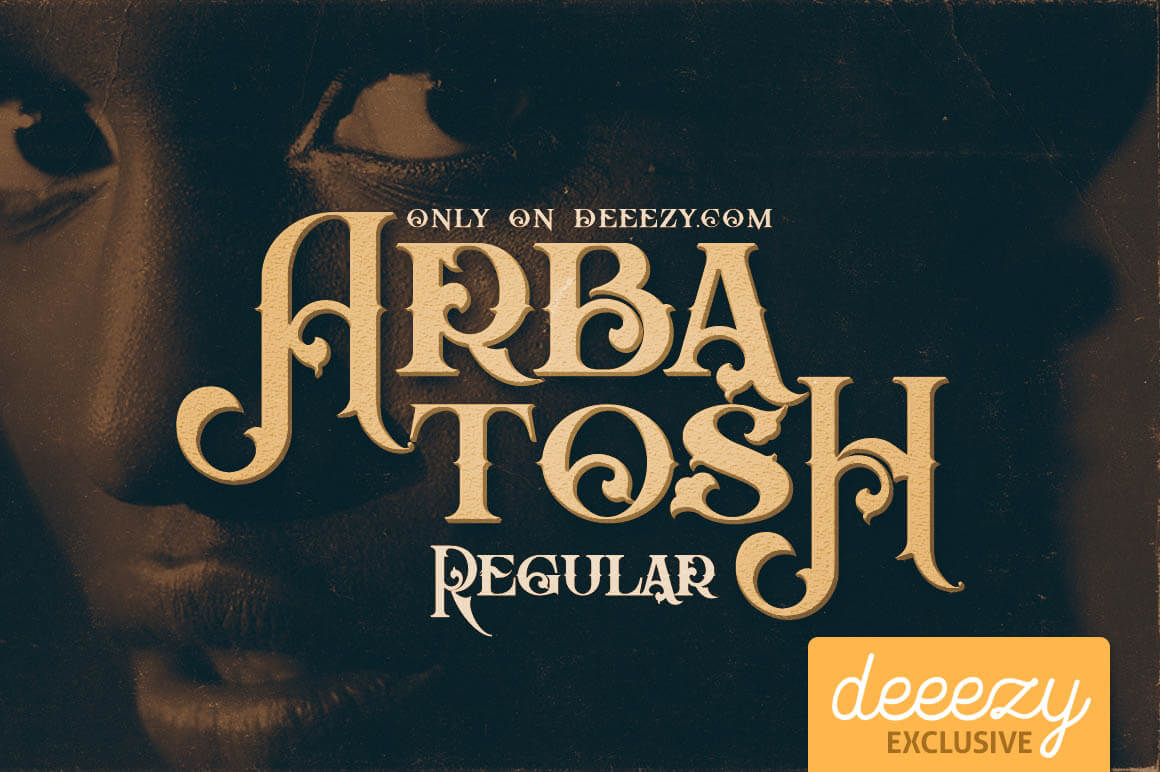
こちらも細部までおしゃれなフォント。大きめに使って、フォントの細かい装飾部分までしっかり見せたいですね。
LaCoste Inline Font
インラインがアクセントになっているセリフ書体。句読点や記号までしっかりおしゃれなのでぜひチェックしてみて!
Octopus Bold Font
縦横の線が同じ太さのセリフ書体。シンプルなので小さく使ってもちゃんと読めて便利なフォントです。
Evolve Inline Font
インラインがおしゃれなフォント。画像のように、文字に大胆にメリハリをつけるとデザインがあか抜けそうですね。
Starship Shadow Font
最初から影がついたデザインの装飾フォント。そのまま使うだけで、すぐにクラシックな雰囲気が出せますよ。
Venomous Shadow Font
こちらも最初から影がついていておしゃれな装飾フォント。短い文章で大きく使うと効果的な書体です。
Magneto Bold Shadow Font
AやWなどが他よりも高いのが特徴のフォント。ただ文字を並べるだけでおしゃれな感じが出ます。装飾性は高いですが、読みやすい書体です。
Hurley Outline Font
横線が極端に細いフォント。小さく使う時はちゃんと読めるか確認が必要でしょう。見出しなどで大きく使うべき書体です。
Royal Guilloche Shadow Font
細部までつい眺めてしまう、クラシックな雰囲気たっぷりの装飾フォント。この書体を使うだけで、かなりデザインが完成するので助かりますね。
Pirate Regular Font
曲線が美しい装飾フォント。そのまま同じ大きさで文字を並べるよりも、思い切り大小の差をつけた方が面白いデザインができそうです。
Napoleon Shadow Font
小文字の「a」や「e」が特徴的な、影つきの装飾フォント。小文字で少し見づらいものがあるので、デザインする時は読めるかどうか必ず確認しましょう。
Westwood Regular Font
「WATNED」の文字に使われそうな西部劇っぽいフォント。横線が太く、安定感のある書体です。
Tracker Italic Inline Font
力強い印象の、インラインのイタリック書体です。クラシック感を強く出したい時に使えそうです。
Flamingo Shadow Font
クラシックな雰囲気の、細めのセリフ書体。レトロな感じを演出したい時に使いたいフォントです。
Star Full Inline Font
繊細なインラインが印象的な装飾フォント。女性向けの媒体で活躍しそうです。
Gatsby Inline – ArtDeco Font
太めのインラインが入った装飾フォント。クラシックでかわいい書体なので、女性向けのデザインによく合うと思います。
Atara Line Font
エレガントだけどシャープな印象の書体。他のシンプルなフォントと組み合わせると、ユニークさがよりひき立ちます。
Annabel Regular Font